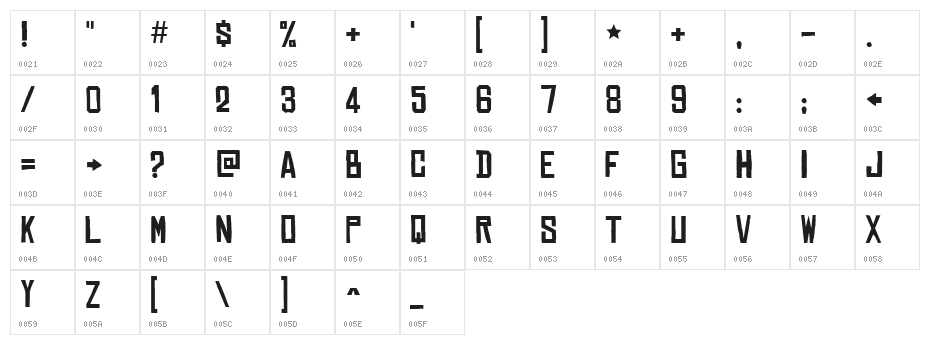
Chinese Rocks Font
| Общий стиль | Vintage, Industrial |
| Рекомендуемые проекты | Ideal for posters, album covers, branding for edgy or industrial-themed products, and any design needing a bold, gritty aesthetic. |